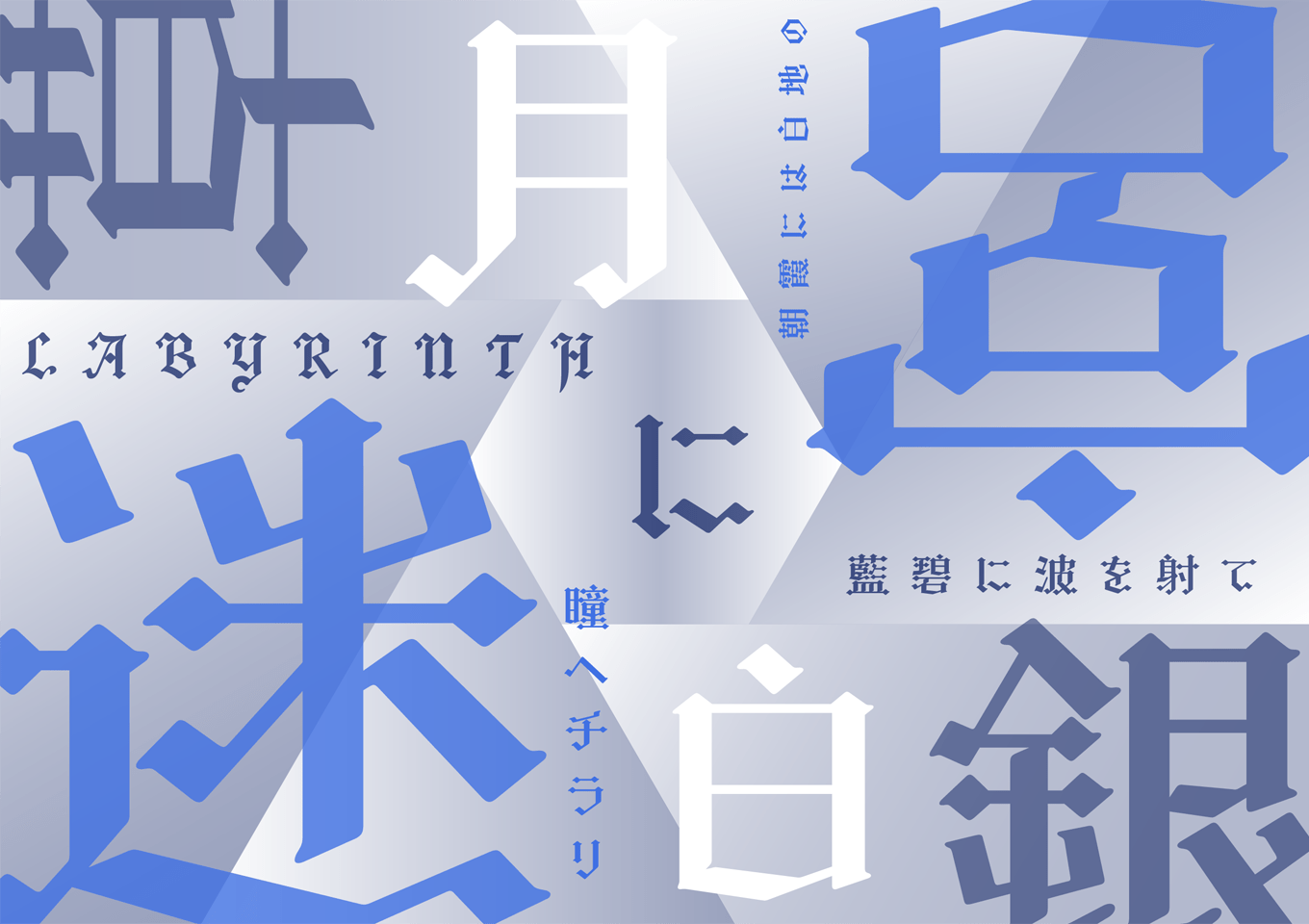
タイプバンクブランドのかな書体「TBかナ-オズ」に漢字を追加した、装飾性の高いブラックレター風のデザイン書体です。平筆で書いたような直線的なストロークを持ちながらも折り返しの角は丸く設計しており、硬くなりすぎないユニークなデザインが特徴です。コミックや書籍装丁などでインパクトのある文字組を実現します。